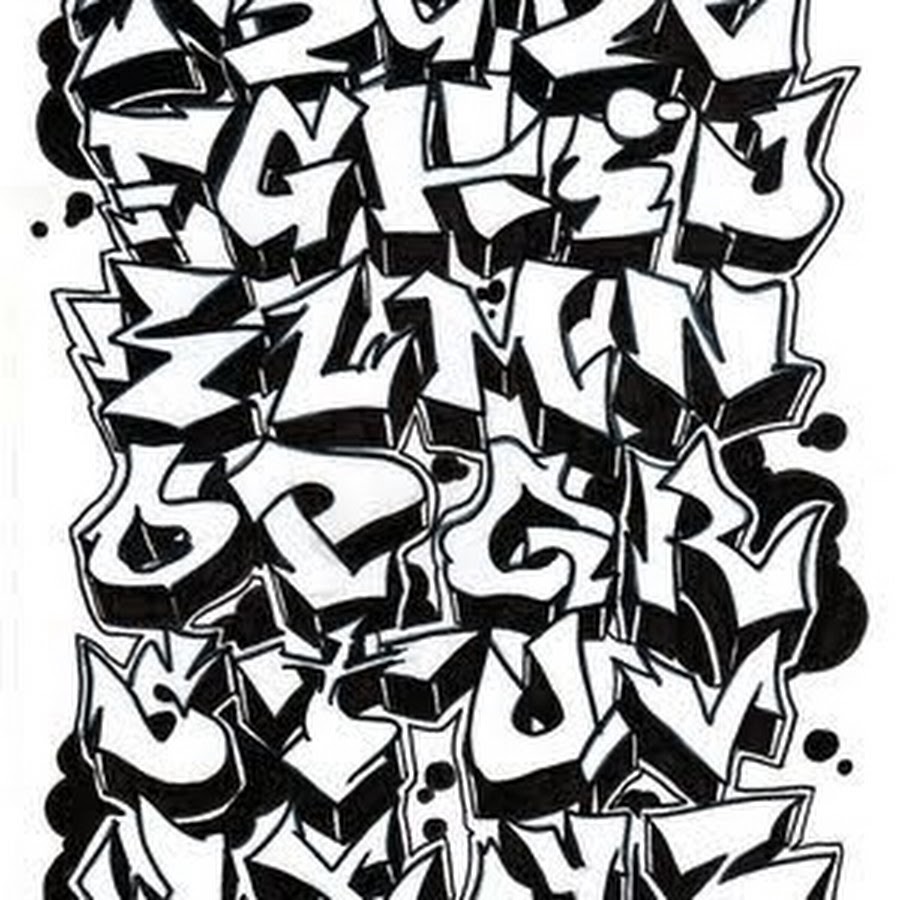
Придумываем граффити шрифт сами.
1) Чтобы изобразить шрифт первым делом пишем простыми печатными буквами свое слово. Следующим этапом следует попробовать изобразить ето же слово но уже не линиями а отдельными формами. При этом следует соблюдать паралельность линий, тоесть паралельные линии должны по всей длинне идти на одинаковом растоянии друг от друга. Толщина отдельных элементов букв должна быть одинаковой (левая и правая ножки буквы «п» должны иметь одинаковую толщину). Пропорции букв тоже должны совпадать. Не следует на начальном этапе пытаться играть с размером букв и делать их разной толщины (всеравно получится не очень). Для удобства рисуйте отдельные элементы пересекающимися друг с другом,потом убирайте лишнии линии и обводите основные. После всех манипуляций у вас получится нечто похожее на буквы на примере (1)
2) После того ка вы оттачили и набросали отдельные буквы, будем собирать их в шрифт.
Далее поманипулировать этой буквой, тоесть просто попробовать поразворачивать букву вокруг ее центра на разные углы. Иногда данный способ дает неплохие результаты. Пример (3) слово EUG, придуманна буква «E» далее эта буква разворачивается на 90 градусов против часовй стрелки, немного дорабатывается и получается буква «U», следующая буква «G» тоже получается из буквы «E» посредством небольших доработок, перемещаем верхний элемент буквы под нижний, нижний слегка увеличиваем. Вот вам шрифт выполненый из букв в одном стиле. 4) После некоторой тренировки с простыми формами букв можно переходить к более сложным, добавляя дополнительные элементы (формы, стрелки и тд), создавая соединения между буквами. На этом этапе главное не переборщить и не забыть, что буква должна оставаться буквой. Не следует навешивать слишком много элементов, слишком сильно до неузнаваемости изменять форму букв, помните в шрифте главное это буквы, доп-формы второстепенны. Так же в процессе экспериментов не забывайте о общей композиции шрифта.
Как рисовать граффити?
Начнем с эскиза. Нарисовать красивый и аккуратный скетч (дословно – набросок, эскиз) – не такая простая работа как может показаться с первого взгляда.
Набивай руку, потом будет проще претворить идеи в жизнь, подобрать всевозможные цветовые переходы, определиться с фоном.
Как я уже говорил, компьютера у меня не было, но я любил заходить в магазин и рассматривать диски. В один из таких моментов я увидел диск на котором был изображен персонаж с баллоном, а над ним было название «Граффити», я тут же побежал домой и рассказал маме и бабушке об этом событии, и так как у меня приближался день рождения, бабушка дала мне денег на него и я пулей полетел обратно в магазин, купил его и отправился к другу у которого был компьютер. На диске было все, что мне было нужно, фотографии, видео, статьи. После полученного заряда информации я стал рисовать еще больше.
Ты можешь описать свой стиль?
Лет 5 назад у меня был такой момент, что мне показалось, что я нашел свой стиль, нашел те формы букв, которые я с легкостью, быстро могу рисовать, как ведет рука. Со временем я понял, что если так и будет продолжаться, то я просто остановлюсь и начал экспериментировать с прямыми линиями, вышло именно то, что делаю сейчас. Стиль это или нет, трудно сказать, посмотрим, что будет дальше.